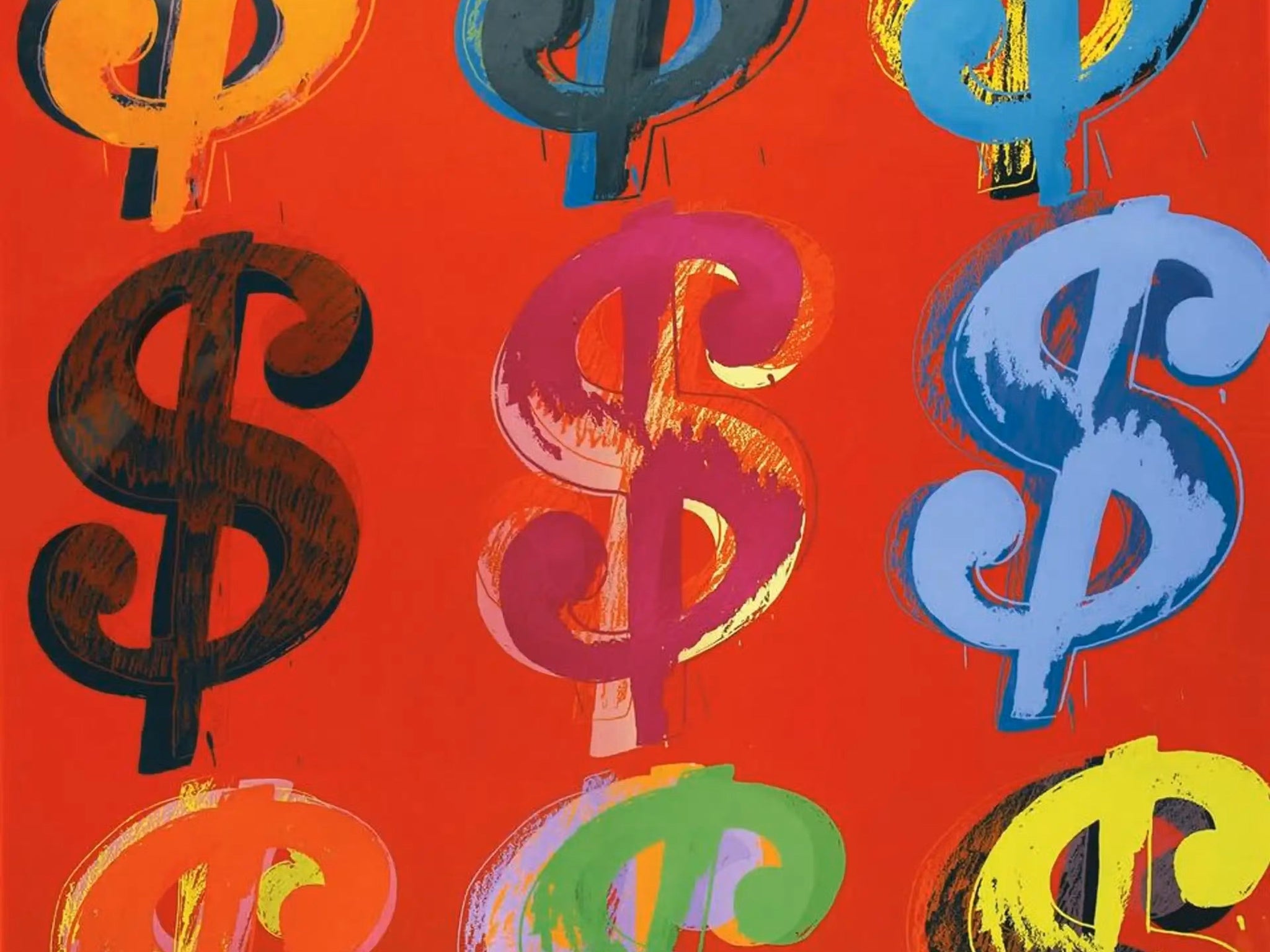
Il suffit de regarder les dessins animés et la culture populaire. Les sacs des braqueurs de banque, les yeux de M. Krabs. Andy Warhol !
Il est synonyme et omniprésent, surtout aux États-Unis bien sûr. Il est intéressant de noter, cependant, qu'il n'a pas commencé comme une invention américaine mais comme une abréviation manuscrite du peso colonial espagnol ou "pièce de huit".
À la fin du XVIIIe siècle, le peso d'argent espagnol circulait largement dans les Amériques, et les comptables écrivaient "Ps" (pesos) là où il y a un "P" majuscule avec un "s" en exposant. Dans leur hâte, ces lettres se sont souvent jointes et, au fil du temps, le P et le S qui se chevauchaient se sont simplifiés en un seul caractère "$". Une histoire souvent répétée attribue au commerçant Oliver Pollock l'utilisation de cette abréviation en 1778, et, en effet, sa lettre de la Nouvelle-Orléans de septembre 1778 montre une forme presque identique au "$". Cependant, la pensée moderne s'accorde à dire que le symbole est simplement né d'abréviations de style latin plutôt que d'un monogramme américain ou d'une image de pièce de monnaie.
À cette époque, la pièce espagnole de real de a ocho (8 reales) – la pièce de huit – servait de modèle au dollar américain. Elle avait cours légal en Grande-Bretagne et en Amérique, et la loi américaine sur la monnaie de 1792 a défini le dollar par son poids pour correspondre au dollar espagnol. La correspondance commerciale des années 1770 montre un "$" utilisé pour désigner le peso ou le dollar espagnol. Dans l'Amérique coloniale, cet argent étranger était si fiable que les premiers billets de papier américains ont même reproduit ses motifs, et il s'est répandu dans le monde entier. La National Numismatic Collection du Smithsonian affirme que, à la fin du XVIIIe siècle, le dollar espagnol était en fait la monnaie mondiale, et les Américains le désignait simplement comme le dollar.
Vers la fin du XVIIIe siècle, le symbole "$" est entré dans l'impression. L'imprimeur de Philadelphie Archibald Binny est crédité de la première impression connue du signe du dollar dans un spécimen typographique de 1797. Le symbole s'est ensuite répandu dans les registres et les journaux. En fait, même en 1686 (beaucoup plus tôt), le comptable britannique John Collins a imprimé un guide des marchands utilisant un glyphe de signe du dollar pour désigner les "dollars", qui à l'époque signifiaient les thalers ou rixdollars (non, je n'en avais pas entendu parler avant de faire cette recherche !). Les premiers documents américains écrivaient "$1" de manière similaire au style britannique "£1" (devant le chiffre plutôt qu'après) pour indiquer les pesos ou les dollars. Au cours du XIXe siècle, la plupart des fondeurs de caractères ont opté pour la variante à une barre comme signe du dollar par défaut pour l'impression en anglais, bien que la forme à deux barres ait continué à être utilisée dans certains endroits, notamment dans les pays de langue portugaise, où elle est appelée cifrão.
Aujourd'hui, la plupart des polices offrent toujours les deux formes (double et simple barre) comme designs alternatifs. Unicode les traite comme des variantes stylistiques du même point de code. En règle générale, le "$ " à barre unique est utilisé pour le dollar américain et la plupart des devises, tandis que le "cifrão" à double barre apparaît dans des contextes liés aux reals portugais ou pour un effet historique. Par exemple, de nombreuses polices à empattement de "style ancien" – comme Baskerville – affichent un "$" à double barre par défaut, tandis que les polices sans empattement plus simples ont une seule barre, ce que l'on peut supposer être pour des raisons de simplicité. Dans l'ensemble, le signe du dollar a bien évolué, passant d'une ligature scribale à un glyphe standard. Ses formes à simple ou double trait restent une question de style et de contexte, laissant la décision finale au concepteur.